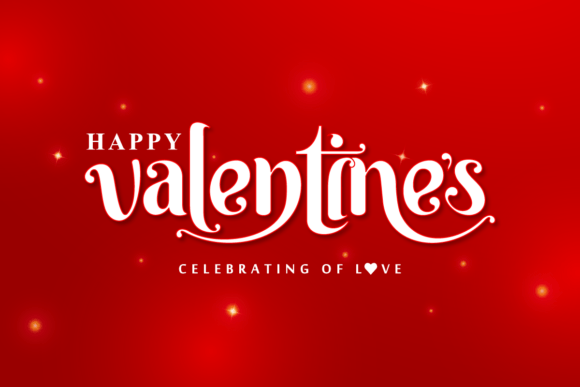
Happy Valentines Day Lettering Fonts
Att hitta rätt designelement kan vara utmanande, men Happy Valentines Day Lettering Fonts erbjuder en exceptionell samling som omedelbart lyfter ditt arbete.
Tillverkad med precision, ger Happy Valentines Day Lettering Fonts rena vektorer, smidig typografi och en kommersiell licens för sinnesfrid.
Oavsett om du skapar POD-produkter (Print on Demand), bröllopsinbjudningar eller grafik för sociala medier, är Happy Valentines Day Lettering Fonts ett perfekt val.